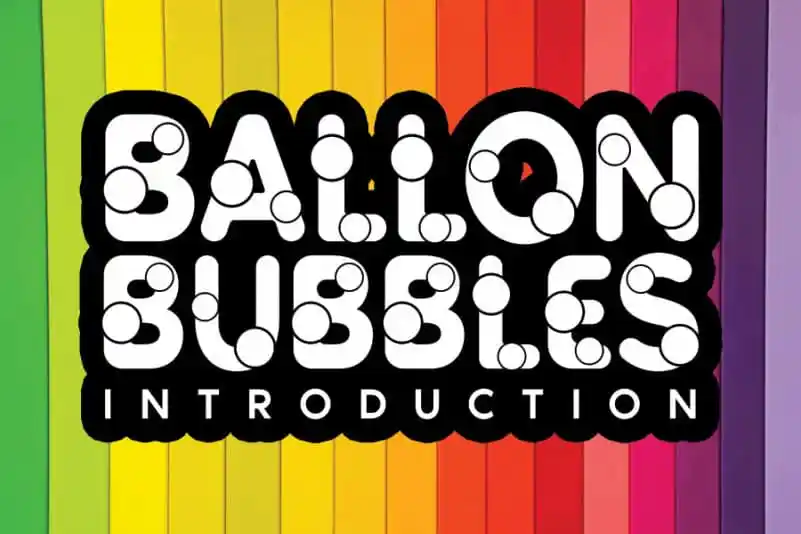
Ballon Bubbles Display Font – Download Grátis
A fonte Ballon Bubbles Display Font é uma escolha ideal para aqueles que desejam tornar seus projetos de crafting ainda mais divertidos e criativos. Com seu look único, ela pode transformar qualquer projeto de hobby ou projeto escolar em um verdadeiro trabalho de arte, especialmente quando usada com sua graça infantil e coragem alegre. Esta fonte é perfeita para quem quer deixar suas criações brincando, animadas e divertidas, criando uma atmosfera que encoraja criatividade e imaginação em todas as idades. Ideal para personalizar anúncios, selos ou qualquer tipo de arte digital, a Ballon Bubbles Display Font é perfeita para quem busca um toque único e inspirador nas suas produções.